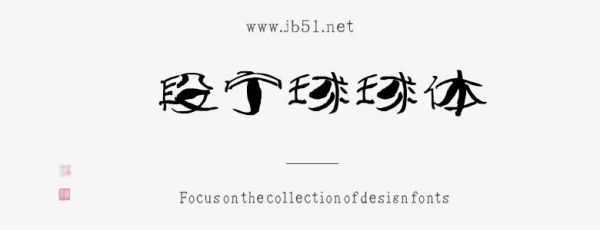
段寧球球體是由段寧字庫(kù)出品的字體,這款字體筆觸略細(xì),書(shū)寫(xiě)飄逸灑脫,具有很好的視覺(jué)感,適合應(yīng)用于藝術(shù)設(shè)計(jì)、平面宣傳設(shè)計(jì)、網(wǎng)頁(yè)設(shè)計(jì),書(shū)法字帖等領(lǐng)域,需要的朋友可以前來(lái)本站下載。